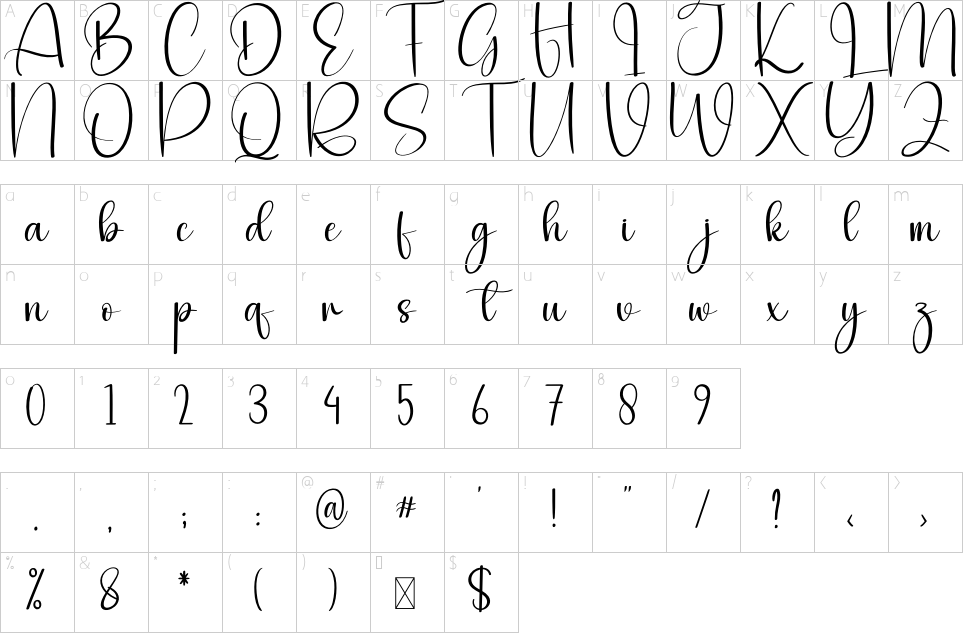
Descubra a encantadora e fluida ‘Angelina Font’, perfeita para tornar seus projetos singulares e charmosos. Desenvolvida pelo talentoso designer william jhordy, a ‘Angelina Font’ é uma peça de arte digital que encanta com suas linhas elegantes e seu equilíbrio perfeito. Com seu design refinado, a ‘Angelina Font’ oferece uma variedade de opções de estilo, fazendo-a uma escolha irresistível para designers gráficos, desenvolvedores de sites e até mesmo blogueiros. Tamanho 288 downloads impressionantes confirmam o seu reconhecimento e popularidade. Baixe a ‘Angelina Font’ para Windows e Mac agora e deixe sua arte falar por você. Aproveite a experiência única desta fonte gratuita e única.